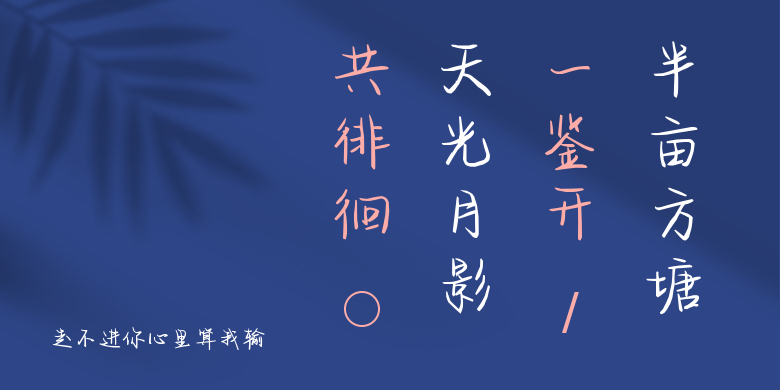
走不进你心里算我输
走不进你心里算我输,这款字体结构工整、笔画清晰,兼顾美观与易读性,适用于标题、正文、海报、包装、LOGO 等多种场景。字形优雅稳定,风格百搭耐看,适配日常排版与创意设计,让文字呈现更舒适、更具质感。走不进你心里算我输一笔一画,皆是细节,以均衡的比例、流畅的线条打造舒适视觉体验,字形端正大气,风格简约现代。无论是商业设计、品牌宣传还是日常排版,都能轻松驾驭,让文字更有格调与力量。走不进你心里算我输字体下载。